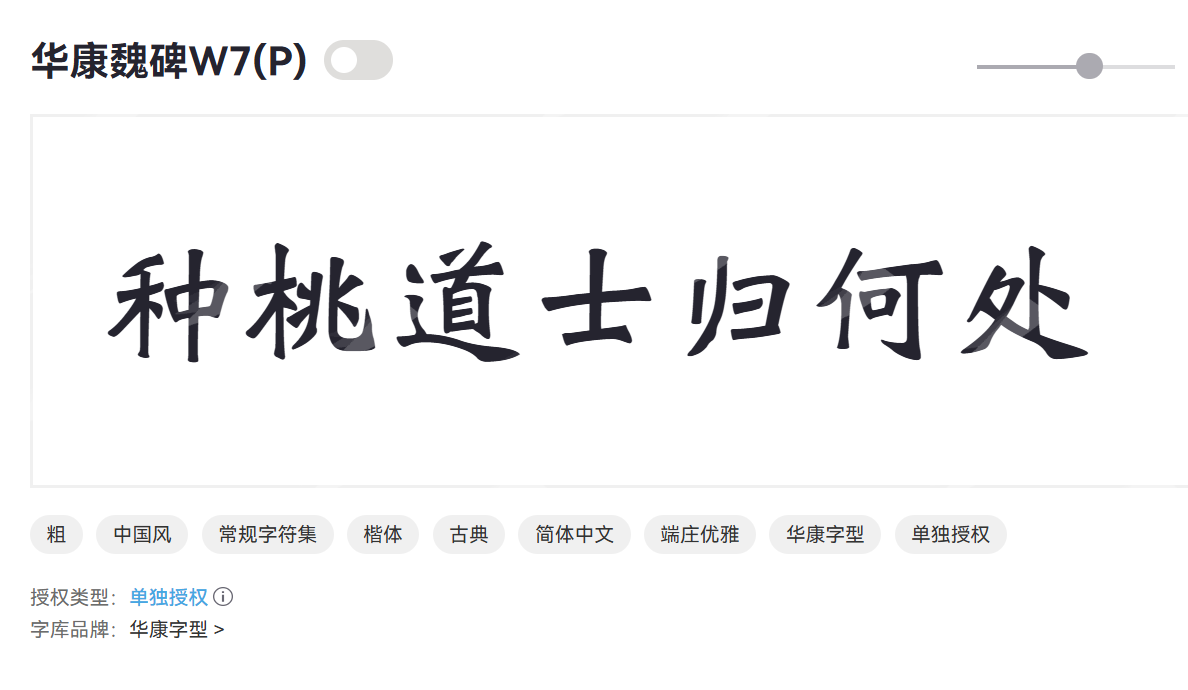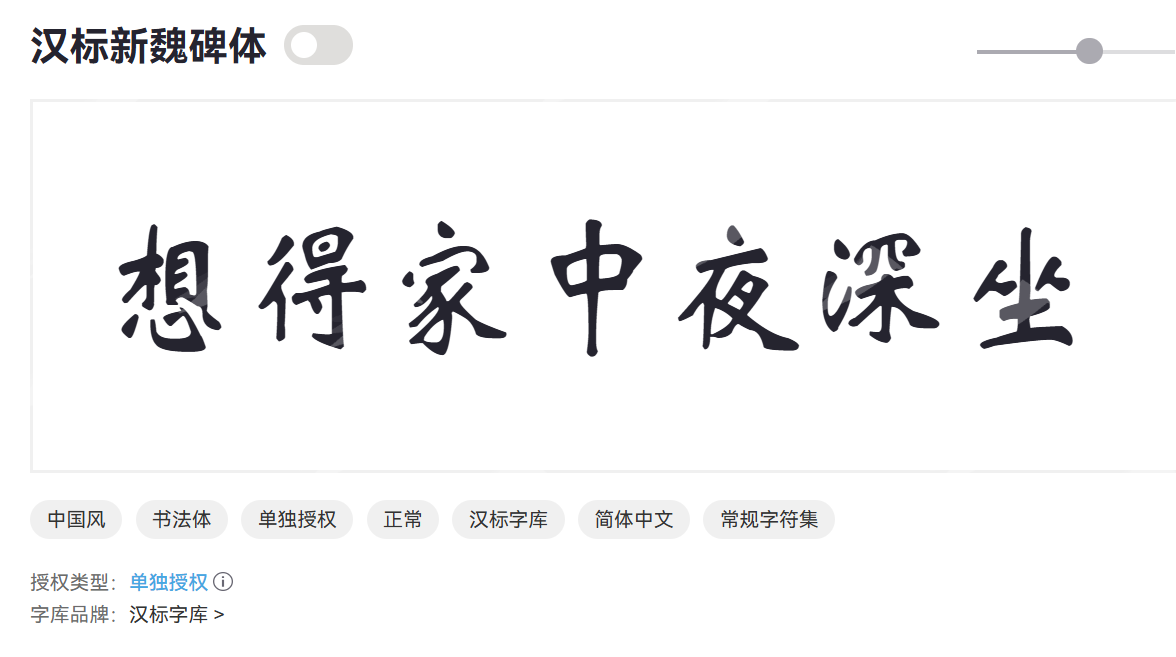
魏碑字体大全,分享6款常用的魏碑字体
魏碑字体,它不仅仅是文字的载体,更是一种力量、一种精神的象征。本文将围绕魏碑字体的特点、使用场景,介绍魏碑字体,让你对它有基础的了解,同时会分享6款常用的魏碑字体,可以在适合的场景尝试这些字体。
什么是魏碑字体?
魏碑字体是指中国北朝时期(特别是魏晋南北朝时期,约公元3世纪至6世纪)在石碑上流行的字体风格。它是在汉隶和草书的基础上,吸收了楷书的特点,并融合了北方民族的豪放、刚健的审美情趣而形成的一种独特字体。
魏碑字体并非单一固定的字体,而是一个大的字体风格类别。它之所以被称为“碑”,是因为其主要载体是古代的石碑。
魏碑字体的特点
魏碑字体的笔画,尤其是横画和竖画,常常呈现出方折、刚劲、有力的特点。横画显得短促而有力,竖画则显得挺拔有力,收笔处常有顿挫感,显得棱角分明。
魏碑字体在结构上,相较于汉隶更加紧凑,但又不像后来的楷书那样规整。它常常显得开张、雄浑、大气,字形结构多变,充满力量感和动感。
魏碑字体的使用场景
- 历史书籍封面、内页排版、博物馆、纪录片、历史剧的片头、片尾字幕
- 书法、国画作品的展览宣传、古风类游戏、影视剧的宣传
- 具有历史感或地域特色的品牌、产品包装
- 个人化与艺术化设计、书法作品的题款、印章设计
6款常用的魏碑字体
华康魏碑
华康魏碑是一款基于中国传统魏碑书法风格设计的字体,由华康公司开发。它融合了古代碑刻的刚劲与现代印刷的清晰度。适合书籍封面和标题设计、海报、展览等设计场景。
华康魏碑灵感来源于北魏时期的碑刻书法,保留了魏碑的典型特征,如笔画方正、结构严谨。这款字体常用于中文排版和设计,以增强传统美感。
汉标新魏碑体
汉标新魏碑体是一款现代改良的魏碑字体,由汉标公司设计。它在传统魏碑基础上加入现代元素,提升了可读性和适用性。汉标新魏碑体结合了古典书法和现代设计理念,旨在为魏碑风格注入新活力。
汉标新魏碑体笔画简化,更适合屏幕显示,在保持刚劲的同时,增加柔和感。适合网站标题和UI设计、广告宣传和社交媒体图文等场景。
义启魏碑体
义启魏碑体基于魏碑书法创作,强调个性化和视觉冲击力。字体设计旨在平衡传统美学与现代应用,为用户提供多样化选择。
义启魏碑体笔画细节丰富,展现手工书法效果,字形略有变形,增加设计趣味。适合艺术和时尚领域,例如艺术海报、插画配文、品牌logo、创意包装、贺卡、邀请函等。
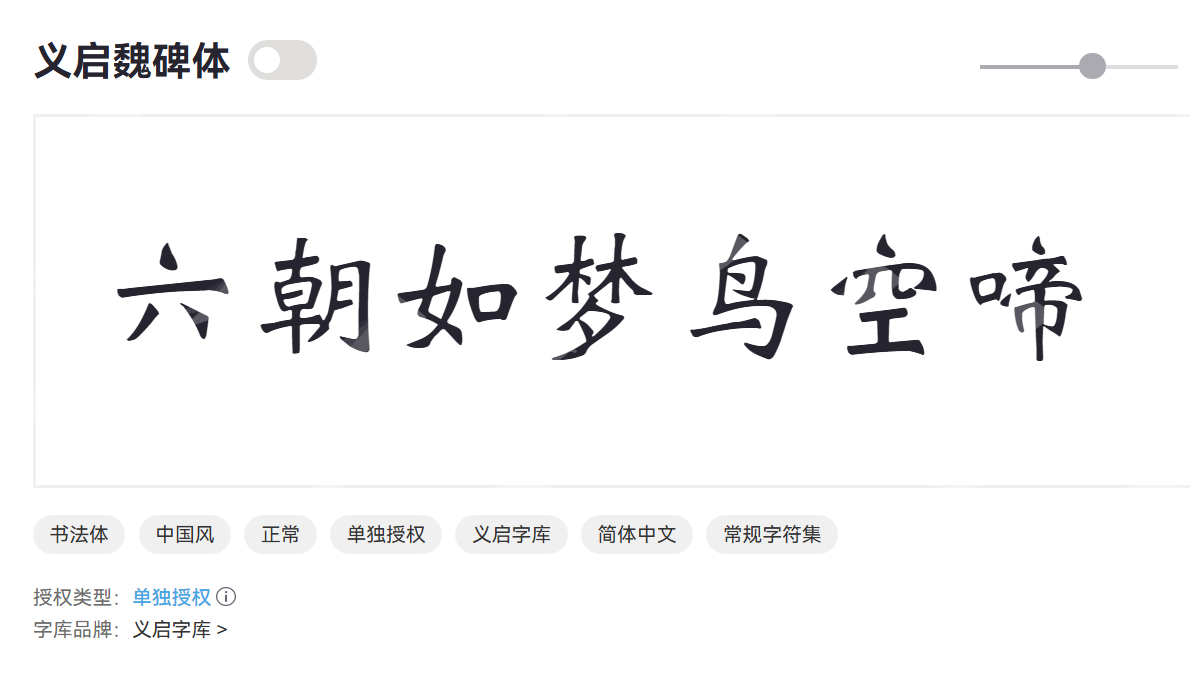
汉仪魏碑
汉仪魏碑是汉仪字库推出的经典魏碑字体,以其权威性和高质量著称。它广泛应用于出版和设计行业,传承了中国书法精髓。
汉仪魏碑字体设计严谨,符合专业排版标准,适合高端应用。比如书籍内文和学术出版物、官方文件和证书设计、博物馆和文化机构宣传品。
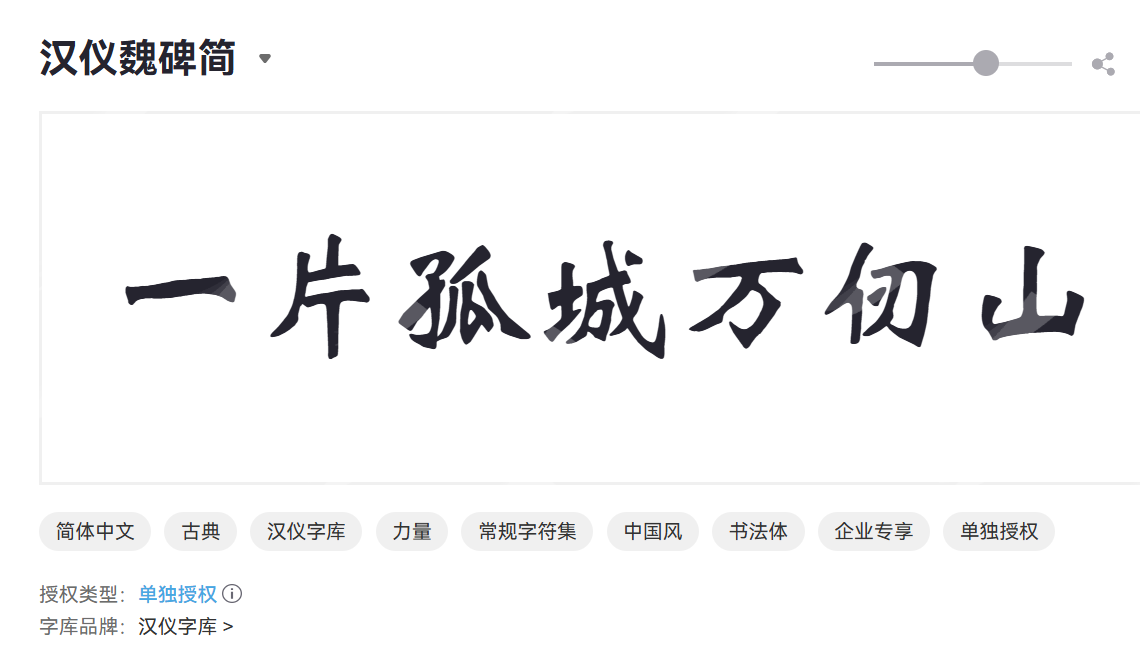
Aa龙师魏楷
Aa龙师魏楷融合了魏碑的刚劲和楷体的流畅,创造出独特的中文字体。设计注重平衡与美感,适用于多种视觉传达场景。
Aa龙师魏楷笔画既有魏碑的硬朗,又有楷体的柔和,字形匀称,适合长篇文本。
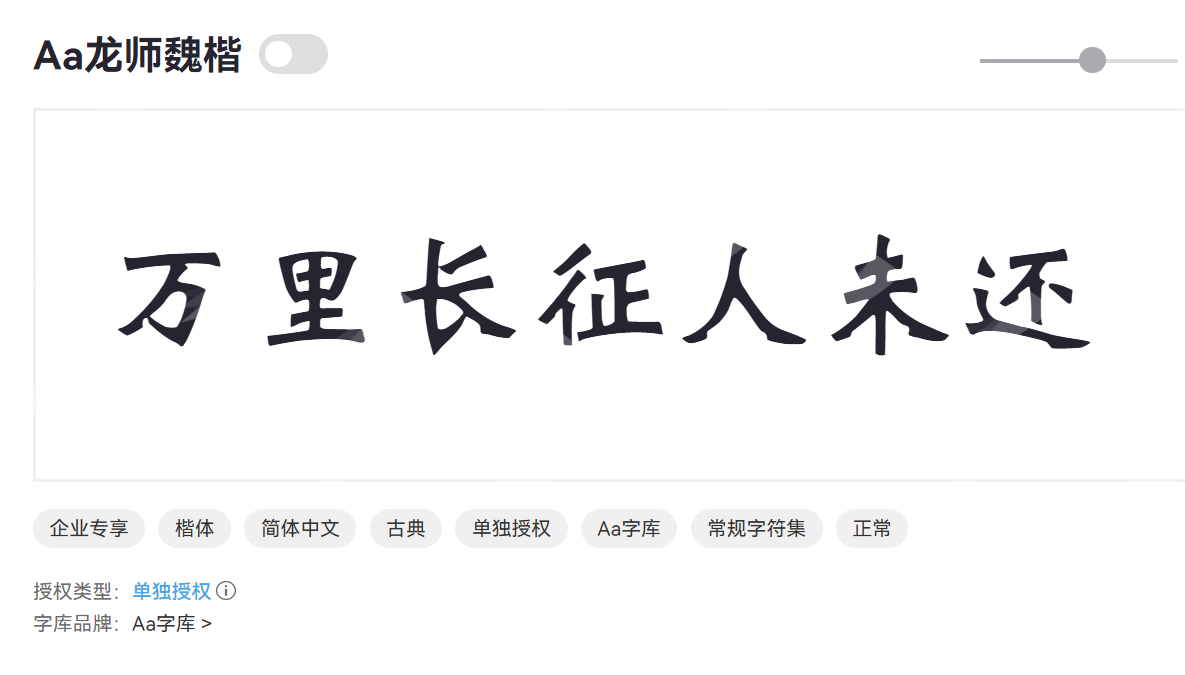
上首碑楷体
上首碑楷体是一款碑刻风格的楷体字体,由上首字库开发。它借鉴了碑刻的粗犷感,同时保持楷体的清晰度,适合强调传统与现代结合的设计。
上首碑楷体以楷书为基础,融入碑刻元素,打造出既有历史感又实用的字体。适用于文化创意和日常排版需求。